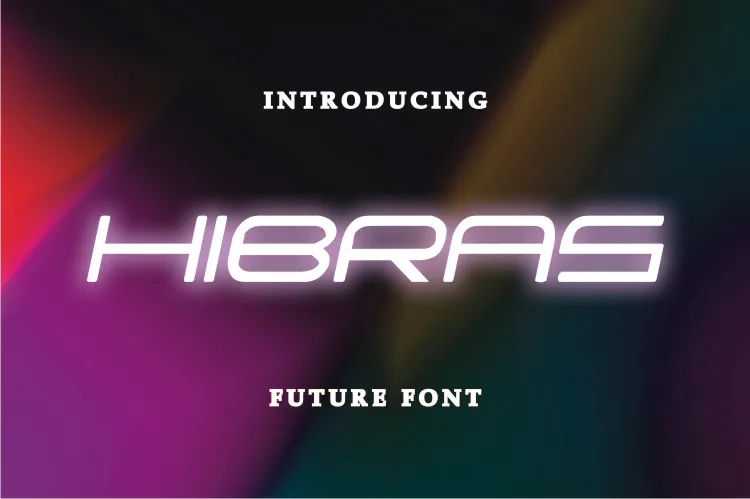
Hibras Font – Download Grátis
A Hibras Font é uma opção perfeita para designers que buscam um ar moderno e criativo. Esta nova família de caracteres, idealmente projetada para os ambientes digitais do dia a dia, destaca-se por sua elegância futurista e versatilidade. Seja você um designer web em busca de uma maneira única de se destacar, ou um profissional de negócios que deseja personalizar seus cards de visita e outros materiais impressos para um toque diferente, a Hibras Font é certamente o item que está procurando. Suave ao olhar, mas repleto de estilo, essa fonte é uma ótima escolha para criar ambientes digitais atrativos e profissionais sem comprometer sua identidade pessoal ou corporativa.